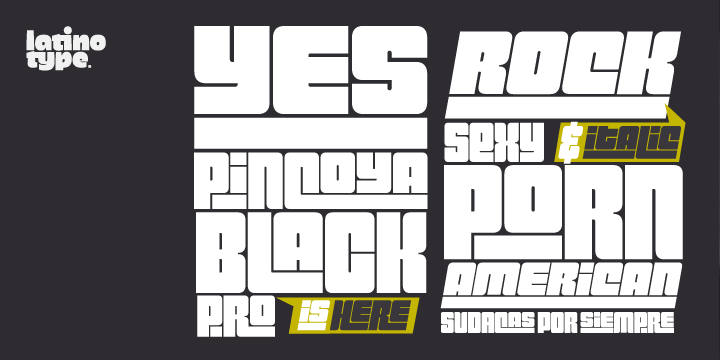
Pincoya Black es una fuente experimental inspirada en el lettering de un afiche de la guerra civil española y con una fuerte influencia de la tipografía llanquihue de Francisco Galvez. Pincoya es una fuente unicase, pero con la opción de variar en los caracteres vocales, los cuales se integran a los caracteres consonantes. http://www.danielhernandez.cl Pincoya Black Pro available in myfonts http://new.myfonts.com/fonts/latinotype/pincoya-black-pro/ |